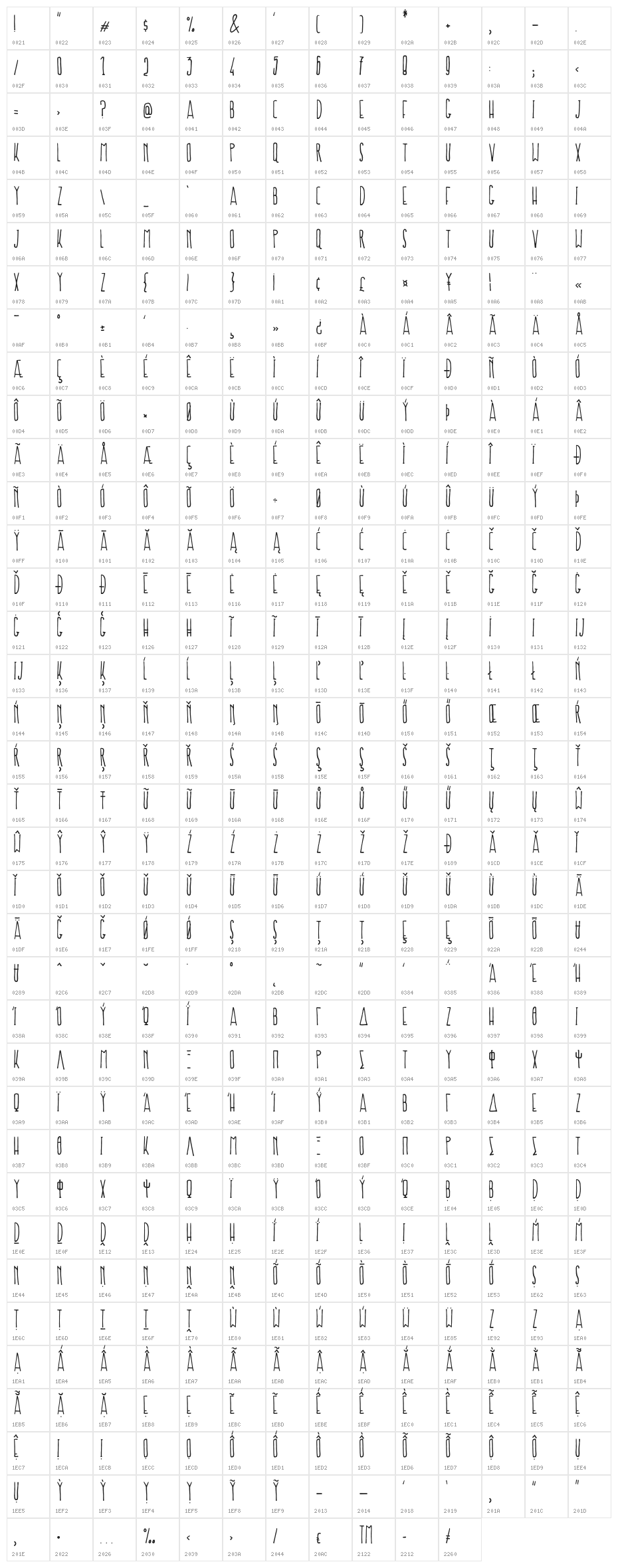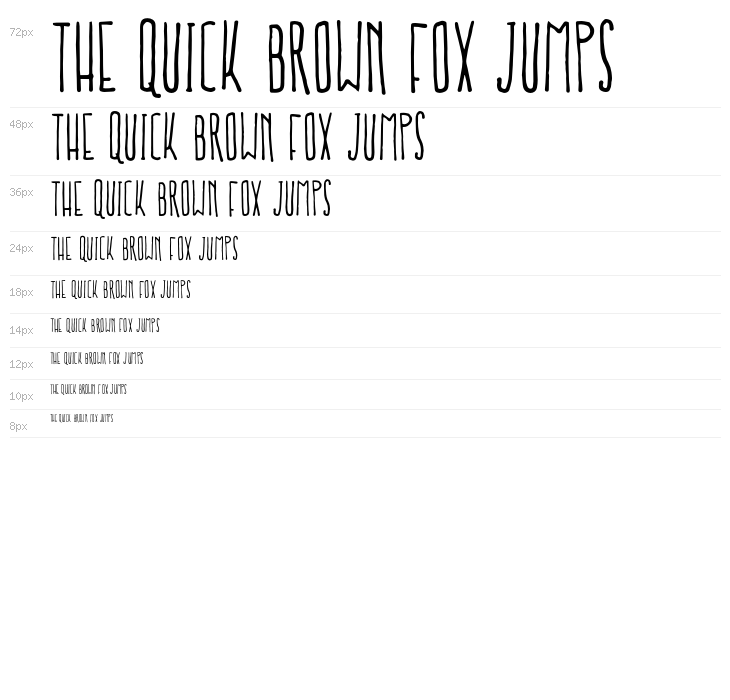
Prokopis Font
| Progetti proposti | Ideal for creative projects such as greeting cards, posters, and branding materials that require a personal, artistic touch. |